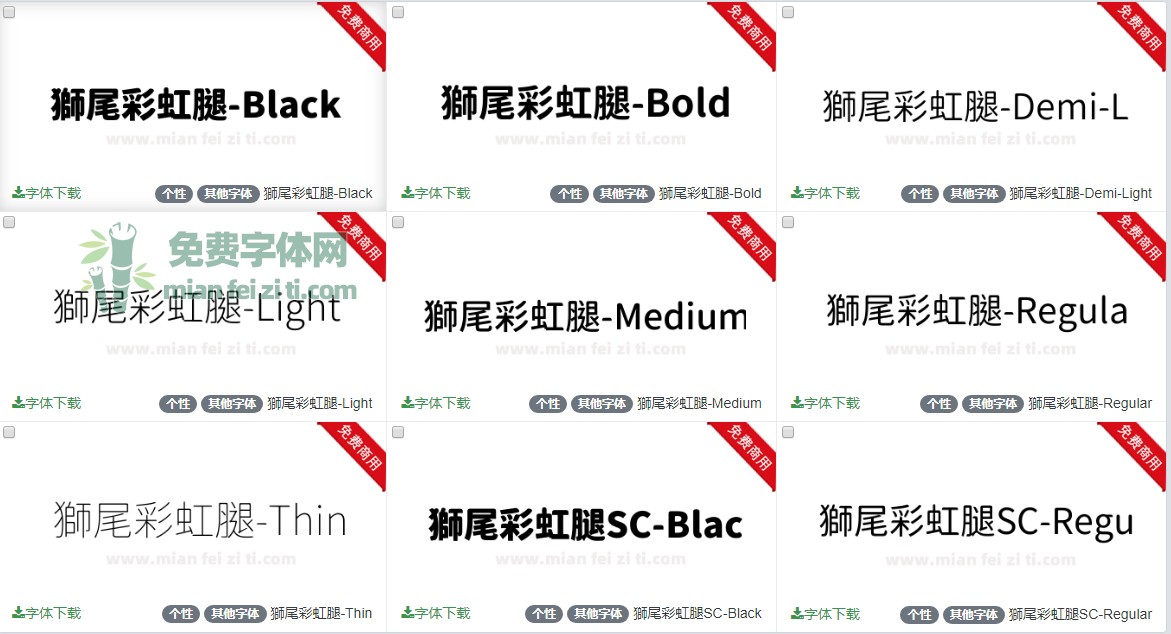
狮尾彩虹腿:把思源黑体的上半边进行变圆改造 免费商用字体字体资讯
狮尾彩虹腿是一款基于思源黑体的上半边进行变圆改造,更加简明现代化的字体。支持简体中文、繁体中文、韩文与日文;欢迎大家自由应用、自由优化、自由改作!
狮尾彩虹腿的特色是,上半边圆体+下半边黑体,一个综合的字体,“口”字的上沿有一点点像彩虹形状,所以Max把这款字体命名为狮尾彩虹腿。由于这款字体是通过程序自动生成,所以有些字可能会出现问题。相较于原版的思源黑体,可能有误删一些符号或不常用的字。
狮尾彩虹腿是基于思源黑体改造而成,所以无论是简体还是繁体基本上都不缺字,并且拥有7个字重。